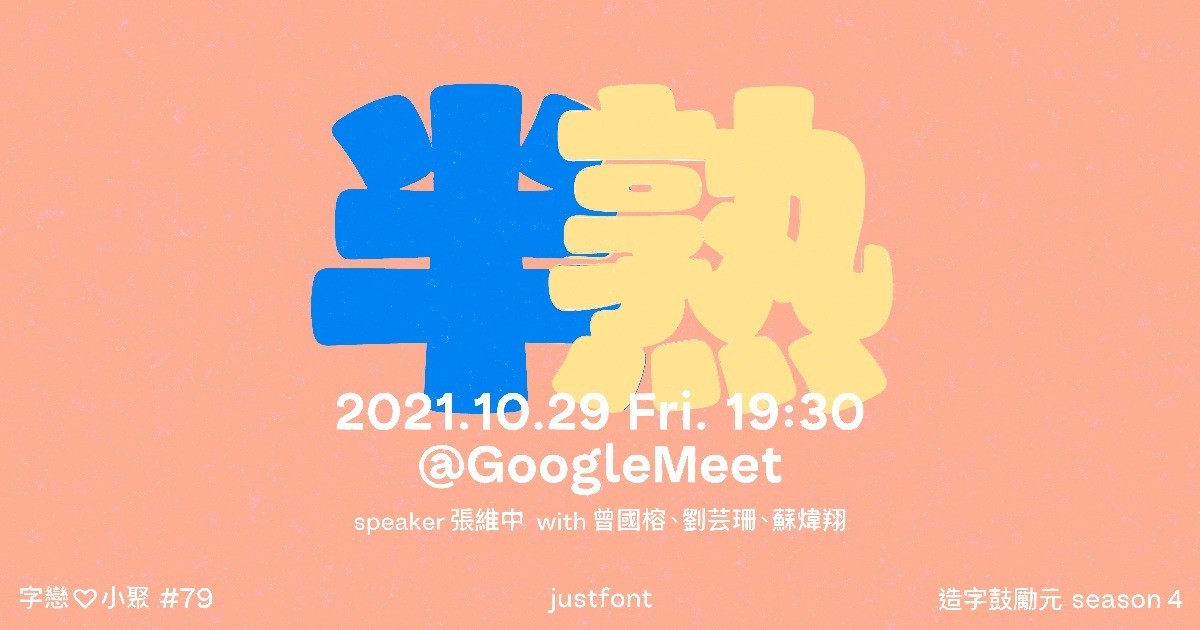
第四屆造字鼓勵元首獎作品即將發表!
從初稿就十分亮眼的提案「黑糖粉粿」
歷經一年多的淬鍊後成為「半熟」⋯⋯
說是半熟,但據本屆造字鼓勵元導師表示:
「都不知道還有哪裡可以輔導了(;´༎ຶД༎ຶ`)」
從造字工法到曲線細節都有不少精彩故事,
敬請期待由設計師維中帶來的分享 (ง๑ •̀_•́)ง
主講:張維中|第四屆造字鼓勵元首獎
與談:曾國榕、劉芸珊、蘇煒翔